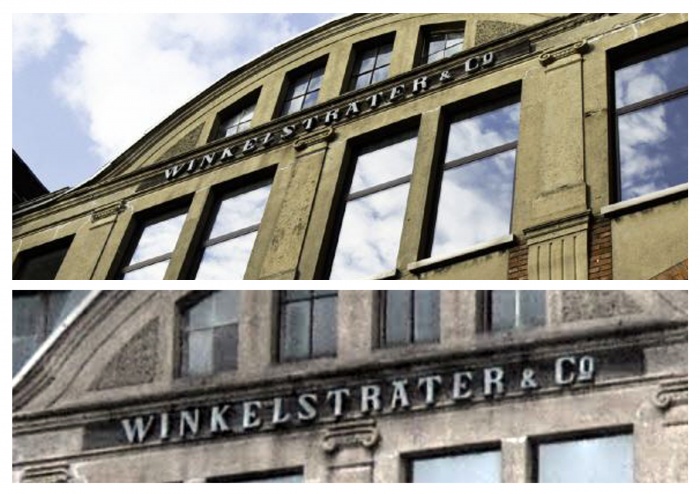
Schriftzug an Fabrik Jahrhundertwende
ich möchte einen zerstörten Schriftzug an einem alten Fabrikgebäude wieder aufleben lassen, kann aber den richtigen Font nicht finden. Es geht grob in Richtung 'Cambria Bold', aber das trifft es nicht so richtig. Hat jemand einen Tip? Dürfte zur Jahrhundertwende 1800-1900 verwendet worden sein.
Es wird sicher keine genaue Entsprechung zu einer heutigen Rechnerschrift geben, nur Annäherungen. Um das wirklich denkmalgerecht zu sanieren, müßte man die Originalschriftzüge nachbauen. Jedenfalls ist das die einzige Möglichkeit, den Charme der Schrift zu erhalten. Wenn man einfach einen ähnlichen Font nimmt, wird das recht steril wirken.
Das wurde damals größtenteils „per Hand“ gemacht.
Am besten, erst mal alles vorhandene sichern. Untersuche das noch vorhandene Material. Evtl. auch den Schatten an der Wand fotografieren, wenn einzelne Lettern inzwischen fehlen. Als nächstes würde ich vorschlagen, einen Schriftgestalter zu beauftragen, den Schriftzug nachzubauen. Gibt es hier in Forum ja auch einige.
Ich finde, der Schriftzug hat auch eine Restauration bzw. Rekonstruktion verdient. Er ist wirklich das Sahnehäubchen auf diesem schönen Gebäude.
Falls die Schrift im Zuge der Sanierung ohnehin demontiert werden muß, könnte man manuell eine Schablone herstellen, nach der die Buchstaben neu gefertigt werden könnten. Dann sollten natürlich auch die originalen Abstände dokumentiert werden, weil sonst die Gefahr besteht, daß ein typographisch unerfahrener Montagebetrieb durch schlechte Abstände alles verdirbt.
Aber natürlich kann man auch anhand eines möglichst guten Photos am Rechner Vectoren bauen, nach denen die Schrift dannn gefräst werden kann.
Leider ist nach Aussage der Baufirma vom Schriftzug nichts mehr übrig, er sei sozusagen bei der Demontage zu Staub zerfallen... nunja!
Eine Schablone wäre toll gewesen und auch die original Buchstaben hätte ich gern in irgendeiner Form erhalten.
Gibt es jemanden hier, der die Schrift anhand der vorliegenden Fotos - andere sind mir nicht bekannt - als Vektorgraphik rekonstruieren kann?
:cry:  Da hat Preßlufthammer-B-B-B-Bernhard wohl mal wieder zugeschlagen. Ein bißchen Erfahrung in der Vectorisierung historischer Vorlagen habe ich ja, wenn auch meist von deutlich besseren Vorlagen. Aber machbar ist das. Ohne mich vordrängeln zu wollen: Ich schicke mal eine PN, dann können wir bei Bedarf mal telephonieren.